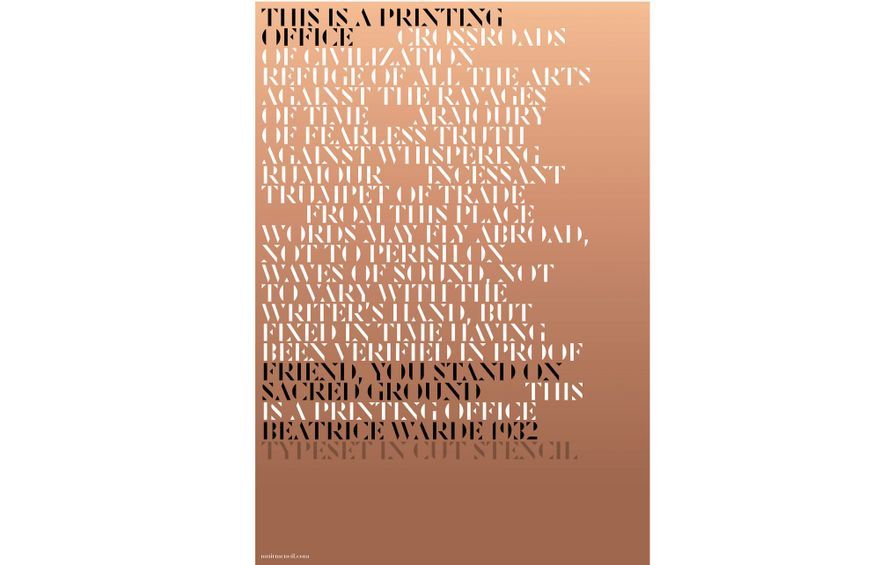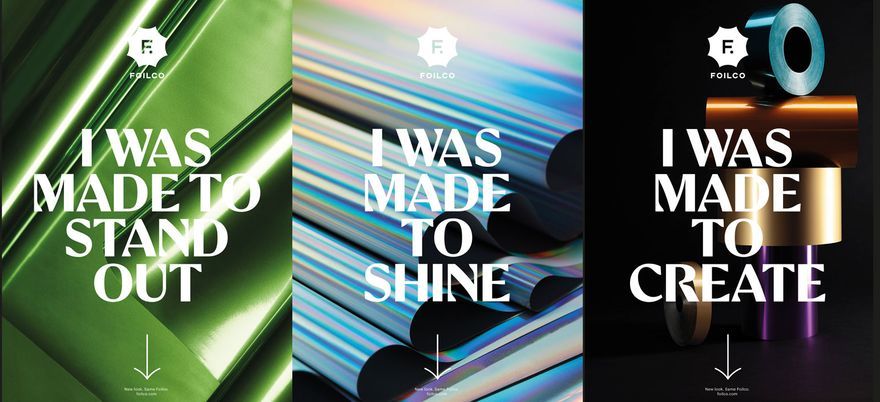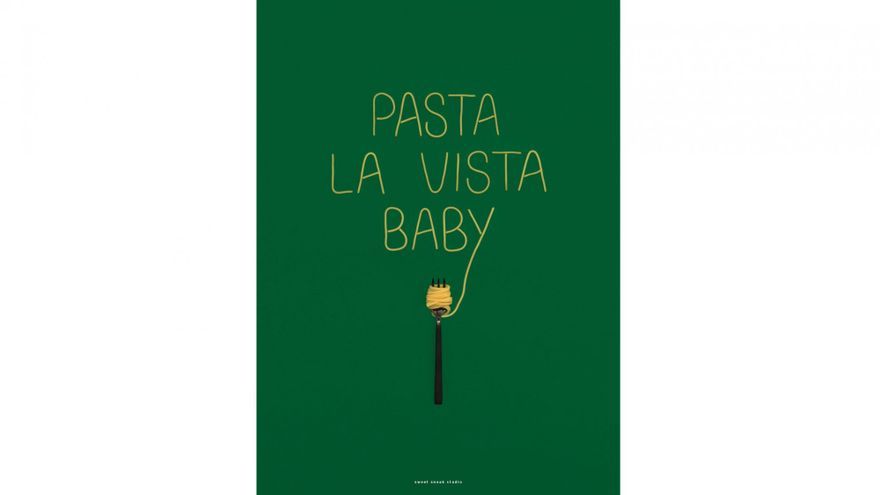
Шрифт vs Гарнитура: полное руководство
В чем разница между шрифтом и семейством шрифтов (гарнитурой)? И действительно ли это имеет значение?
Дискуссия «шрифт vs семейство шрифтов» является напоминанием о том, что терминология отрасли со временем меняется. В большинстве случаев эти два слова взаимозаменяемы, и это не является проблемой. Но на техническом уровне слова «шрифт» и «семейство шрифтов»(гарнитура) действительно имеют разные значения, очень важен контекст использования этих терминов.
Давайте обратимся к истории слов "шрифт" и "семейство шрифтов", как терминов типографики и графического дизайна, и мы раз и навсегда уладим эти дебаты.
Шрифт vs Семейство шрифтов: в чем же разница?
Студия DBD попросила производителя шрифтов F37 создать на заказ шрифт для своего ребрендинга Foilco
Основное различие между «шрифтом» и «гарнитурой» (семейством шрифтов) заключается в том, что первое является частью второго. Helvetica - это гарнитура - полный набор символов sans serif с общим характерным дизайном. Тем не менее, он состоит из целой коллекции шрифтов, каждый из которых имеет определенную толщину, стиль и размер, различные уровни плотности и курсив.
Поскольку большинство дизайнеров привыкли работать на Mac, где можно сразу установить шрифты, а затем выбирать их из меню «Шрифт», мы склонны использовать слово «шрифт» в обычном разговоре, но если исполнительный креативный директор спросит вас, какой шрифт вы использовали в проекте, то он хочет знать точные детали. В этом случае, Helvetica была бы гарнитурой, выбранной для проекта, но шрифт мог бы быть Helvetica Regular 9.
В определенных случаях и контекстах знание точного названия шрифта имеет большое значение. Эти познания пригодятся вам не только в беседе с профессиональным типографом. Выбор нужного, правильного шрифта при кодировании приложения для определенного типа дисплея сыграет в вашу пользу.
Рекомендации бренда (см. наш любимый style guides) являются еще одним пунктом, по которому дизайнеры выбирают шрифты определенного размера и толщины. Все эти нюансы должны поддерживать эстетику бренда, задуманную дизайнерами. В сфере упаковки товара существуют некоторые правила защиты прав потребителей, которых необходимо придерживаться. Например, законодательство ЕС установил минимальный размер текста для пункта "состав продукта".
Большинство людей в наши дни часто используют термины «шрифт» и «гарнитура» взаимозаменяемо
Dave Sedgwick
Тем не менее, в большинстве случаев даже опытные дизайнеры путаются между этими терминами, и нам не стыдно признать, что это происходит даже в Creative Bloq.
«Возможно, это кощунство, но я не уверен, что я когда-либо знал разницу», - говорит Дейв Седжвик, основатель Studio DBD в Манчестере. «Для большинства людей в наши дни термины «шрифт» и «гарнитура» взаимозаменяемы, и большинство клиентов, также не понимают разницы, поэтому, когда мы рассказываем о шрифтах клиентам, мы используем простую, понятную терминологию, которая ничего не усложняет».
И он прав. Мы выбираем гарнитуру (семейство шрифтов) из-за общих эстетических качеств. Затем мы выбираем конкретный, точный шрифт, устанавливая его размер, ширину, стиль и иногда набор символов, такой как римский, кириллический или греческий. Допустим, вам может понравиться гарнитура Futura из-за его модернистского внешнего вида, и поэтому шрифт, который вы использовали для подписей на вашем сайте - Futura Condensed Extra Bold 8. В данном случае, шрифт - песня, а гарнитура - исполнитель.
Шрифт vs Семейство шрифтов: история
Гарнитура Cut от MuirMcNeil - это модернистское почтение гарнитур XVIII и XIX веков, таких как Didot
Суть разницы между шрифтом и гарнитурой корнями уходит в историю печати. Само слово «шрифт» происходит от французского «fonte», что означает отливка из металла. Раньше отливали целые наборы металлических букв, чтобы создать шрифт. Шрифты, изготовленные в одном дизайне составляют гарнитуру. В коробочке, с определенным шрифтом, было два отделения - один для прописных и один для строчных букв - отсюда верхний и нижний регистр. Блоки текста собирались буква за буквой, чтобы сформировать макет страницы, который затем смачивался чернилами и придавливался к бумаге для печати.
С появлением цифрового набора текста большая часть терминологии «горячего металла» была сохранена, но контекст и возможности полностью изменились. В современных терминах, на самом деле нет никакого различия между шрифтом и гарнитурой. Если на вашем компьютере установлены данные о шрифтах Helvetica, вы сможете отобразить всю гарнитуру. Каждая буква полностью масштабируема, основываясь на одинаковых векторных формулах.
Причина, по которой мы сфокусированы лишь на термине "шрифт", в основном связана с приложениями для настольных издательских систем и обработки текстов, которые имеют меню Font. Когда вы щелкаете по нему, вы получаете список шрифтов - Arial, Baskerville, Caslon и т. д. - там же вы выбираете специфику шрифта - например, Medium Italic 16.